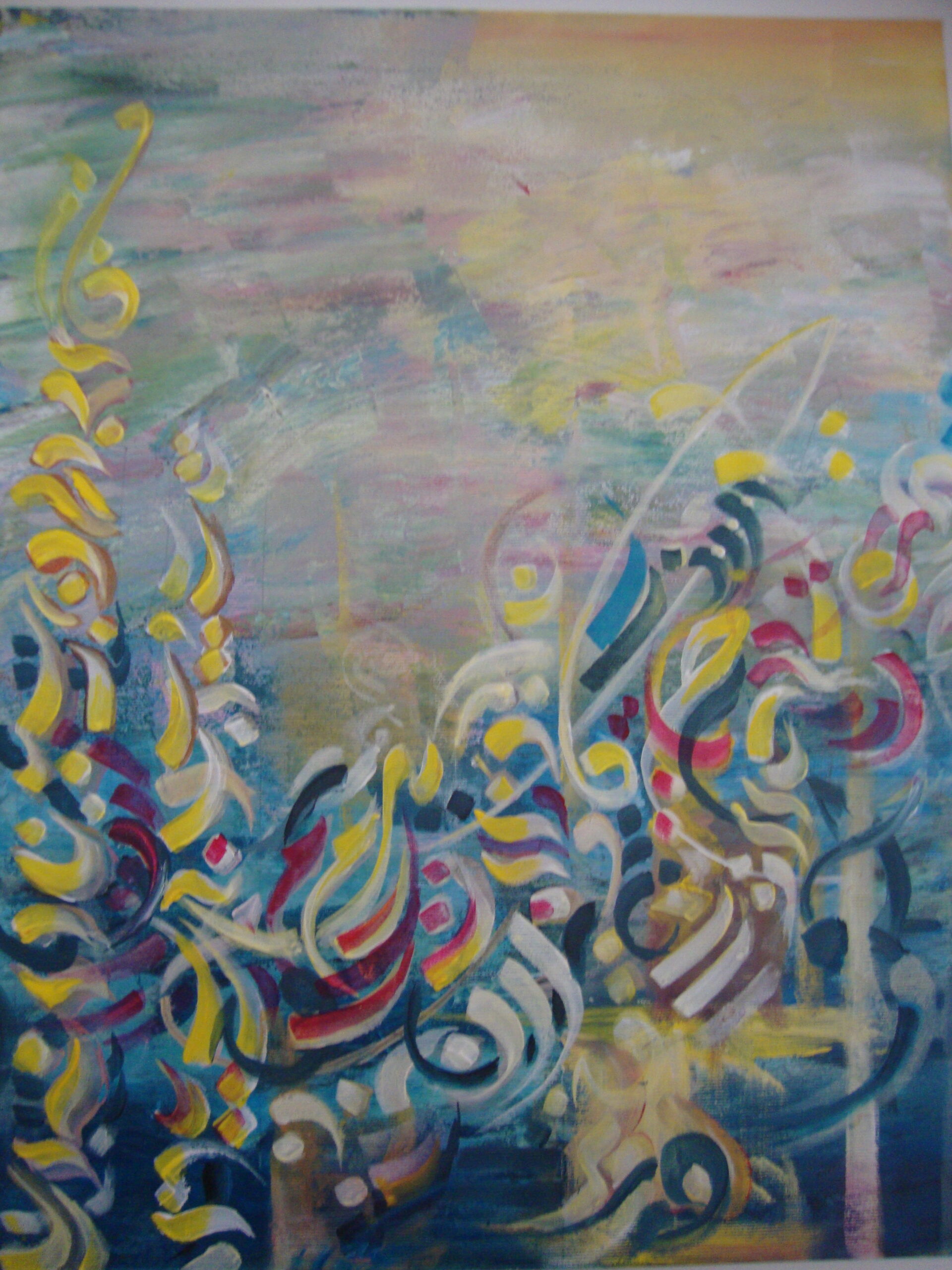
تعتمد تجربة الحروفية على مبدأ، التكرار والتجاوز والصعود بالتجرية الحسية إلى أقصى أبعادها الروحانية، معتمدة استراتيجيات جمالية تتعلق بالزخرفة وتكويناتها المتعددة، متخذة مكاناً وسطاً بين الزخرفة والفن التشكيلي أو هي فن تشكيلي يستلهم الزخارف لاسيما الخطية، وهي تعتمد التكرار كمعطى تراثي وفي الوقت ذاته، معطى تزخر به الفنون المعاصرة، بكل أنواعها حتى الأدائية منها، لكن المقاربة قد تختلف في منطلقاتها المفهومية أو التشكيلية والحضارية للفنون المعاصرة والفنون الإسلامية، فالتكرار له أصل في التصوف الإسلامي أيضاً، وهو سمة تميزه، وهو لا يعمل كإعادة ميكانيكية، بل كفعل انمحاء تدريجي للذات الفردية وانفتاح على المطلق، وهو ما يجعل التكرار ممارسة أنطولوجية بقدر ما هو ممارسة روحية. فيغدو التكرار وسيطًا بين المحسوس واللامرئي.